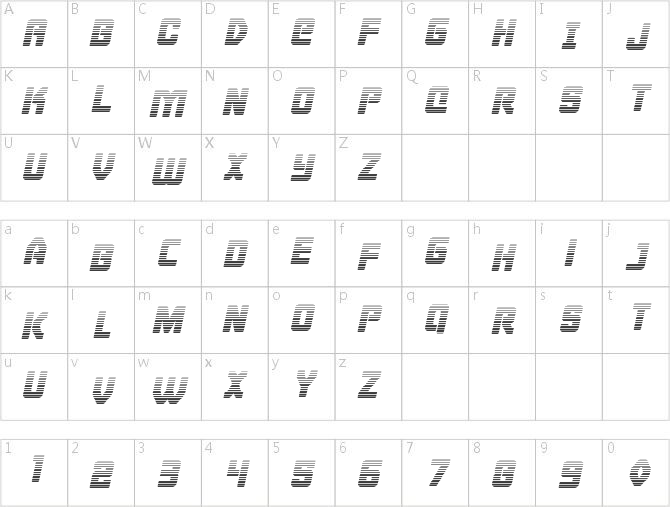
Cyborg Rooster Gradient Italic 詳情頁
Cyborg Rooster Gradient Italic字體字庫是一款讓人賞心悅目、百看不厭的英文字體,適合各類廣告和產(chǎn)品包裝設(shè)計(jì)應(yīng)用,字體大小0.09MB,格式為ttf字體,上傳用戶是錦程正陽,作者/版權(quán)方為未知